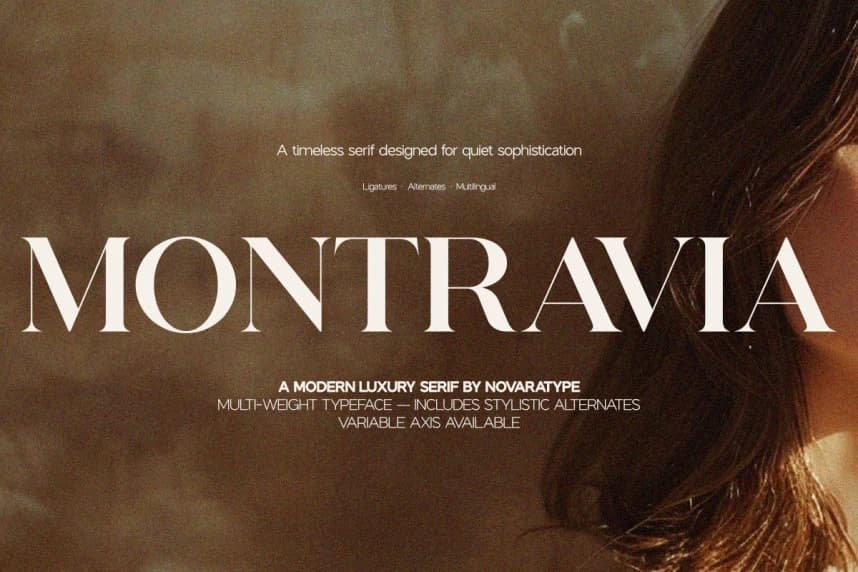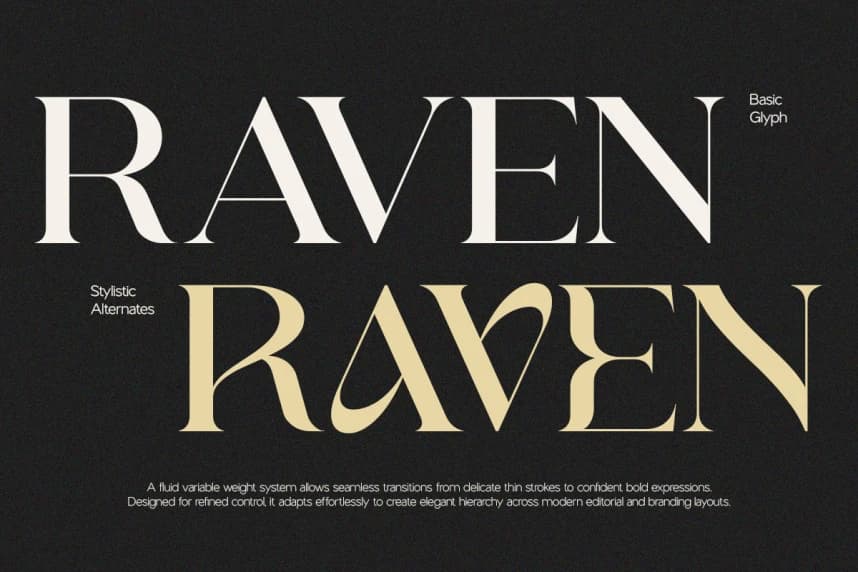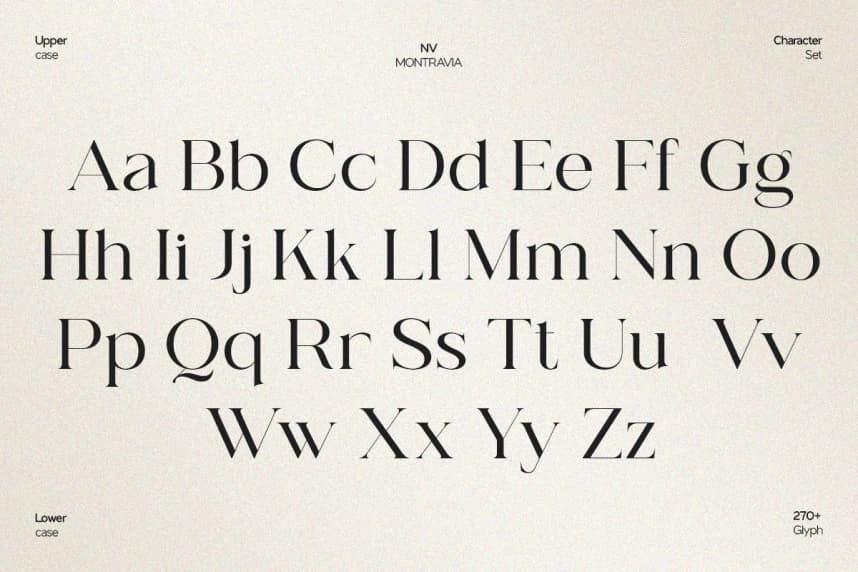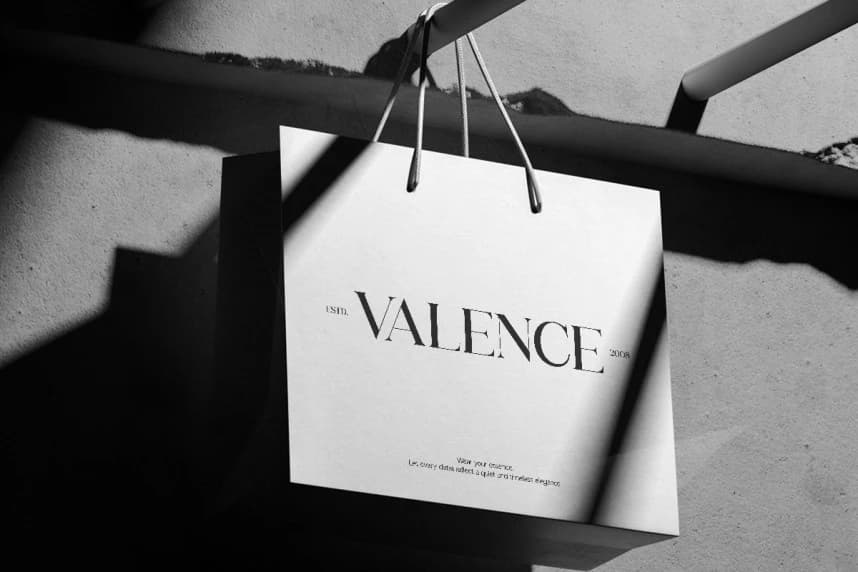
NV MONTRAVIA – Elegant Serif Font Family
NV MONTRAVIA Elegant Serif Font Family, zarafet, incelik ve zamansız güzelliği somutlaştırmak üzere tasarlanmış sofistike bir serif tip sistemi olarak öne çıkar. NovaraType tarafından geliştirilen NV Montravia, yüksek kontrastlı hatları zarif oranlarla bir araya getirir—bu da onu lüks markalaşma, mo
NV MONTRAVIA Elegant Serif Font Family, zarafeti, inceliği ve zamansız güzelliği somutlaştırmak üzere tasarlanmış sofistike bir serif yazı sistemi. NovaraType tarafından geliştirilen NV Montravia, yüksek kontrastlı çizgileri zarif oranlarla bir araya getirerek lüks markalaşma, moda editoryalleri, üst düzey ambalaj ve premium görsel kimlikler için mükemmel bir seçenek haline getiriyor.
NV MONTRAVIA – Elegant Serif